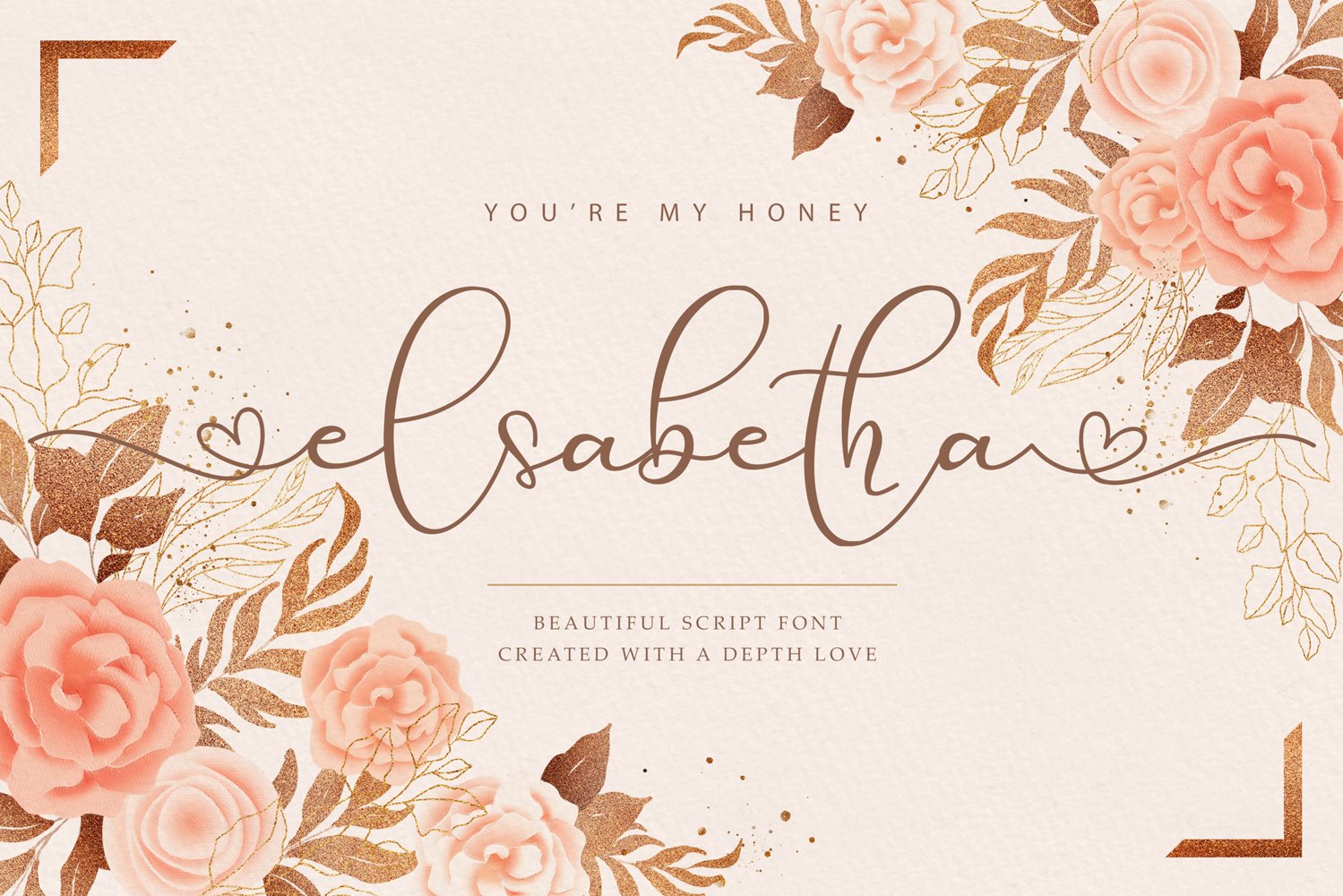
Fontbundles Elsabetha Font
[Fontbundles] Elsaba Font
Эльзабета - это нежный, элегантный и струящийся рукописный шрифт.
Он имеет красивые и хорошо сбалансированные символы, и, как результат, он соответствует широкому кругу дизайнов.
Шрифт эльзабеты отличается разнообразием базовой линии, плавными линиями, великолепными глифами и потрясающими чередованиями.
Добавьте его к вашим самым творческим идеям и заметьте, как он их воплощает!